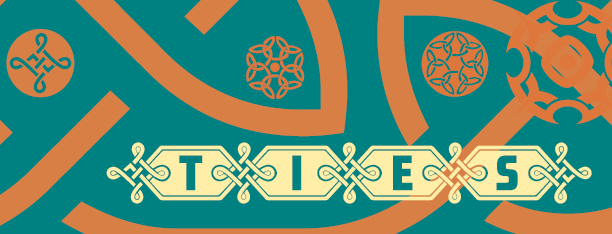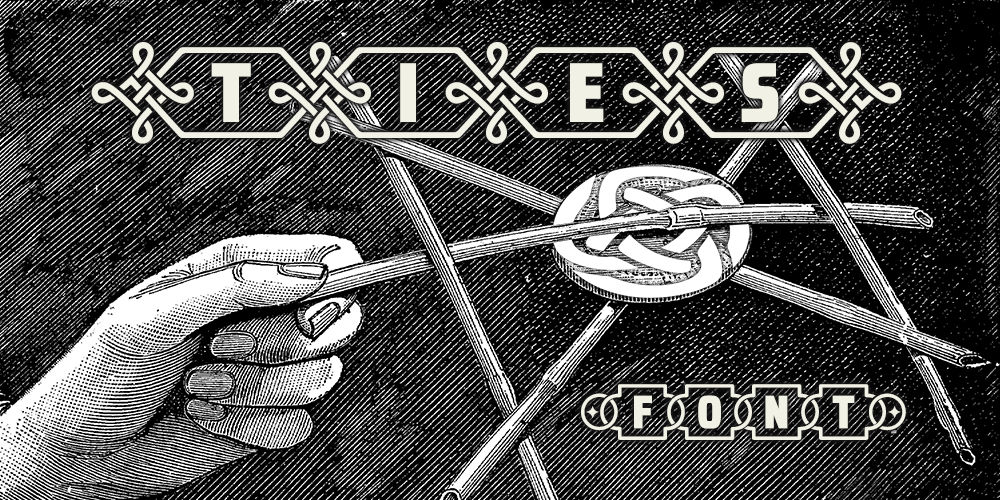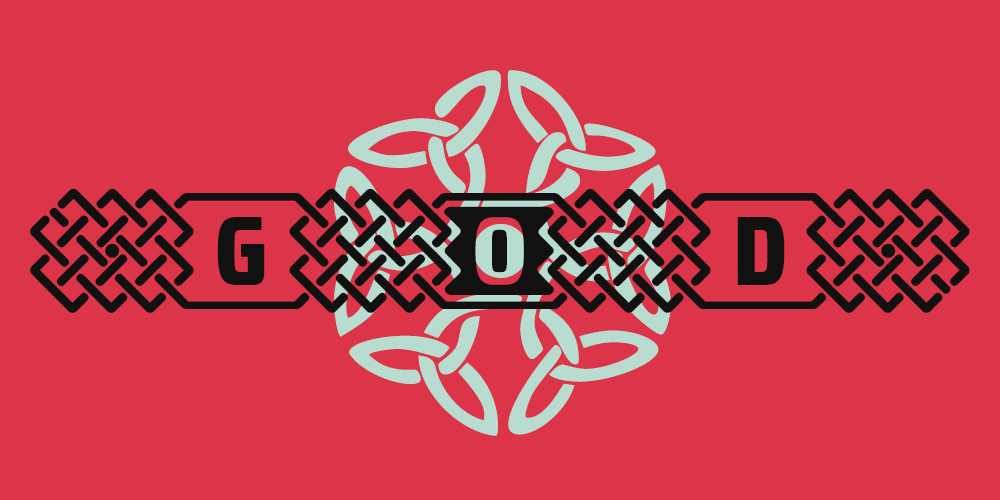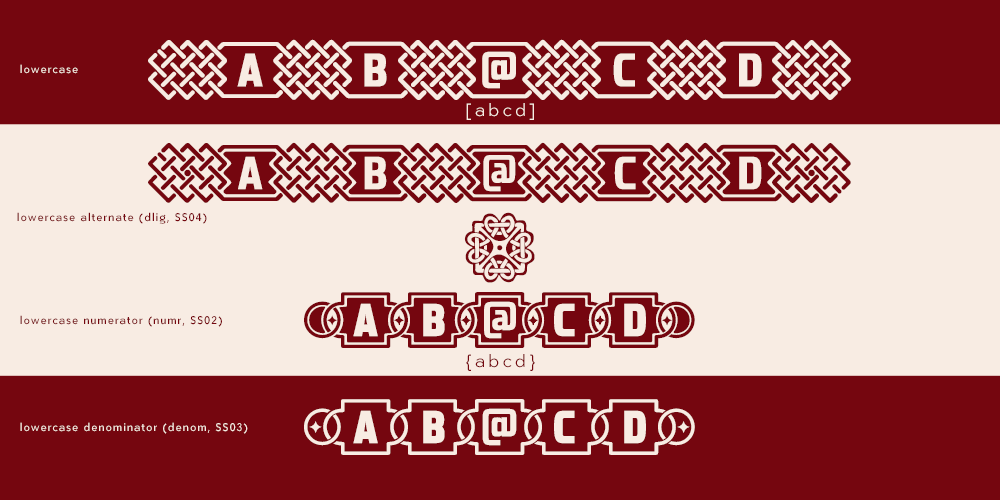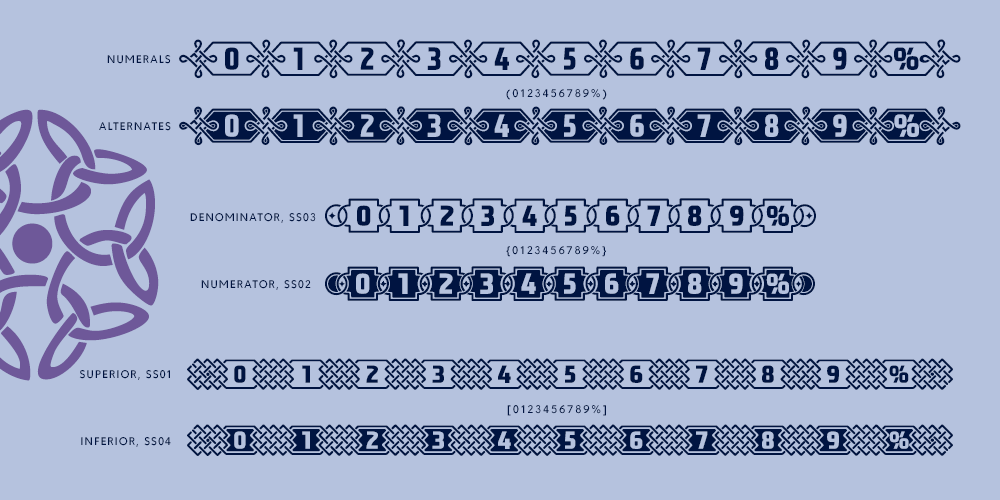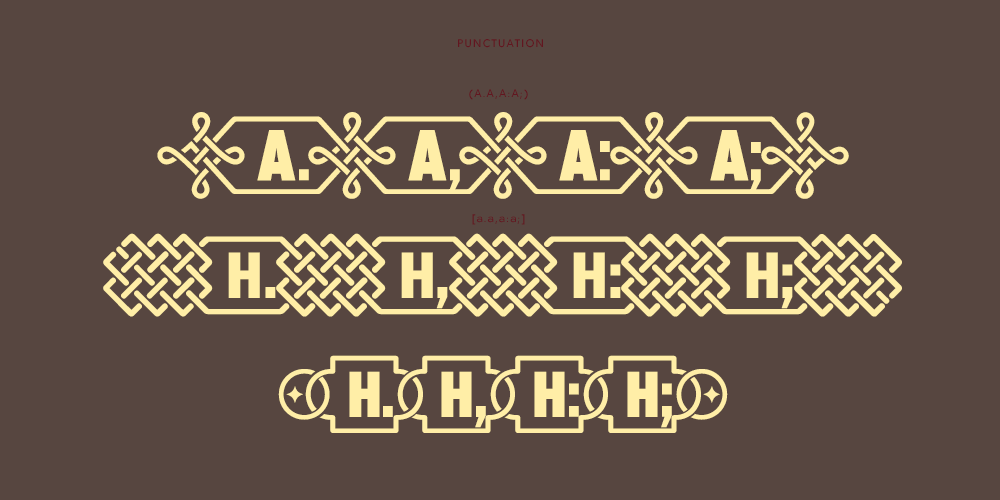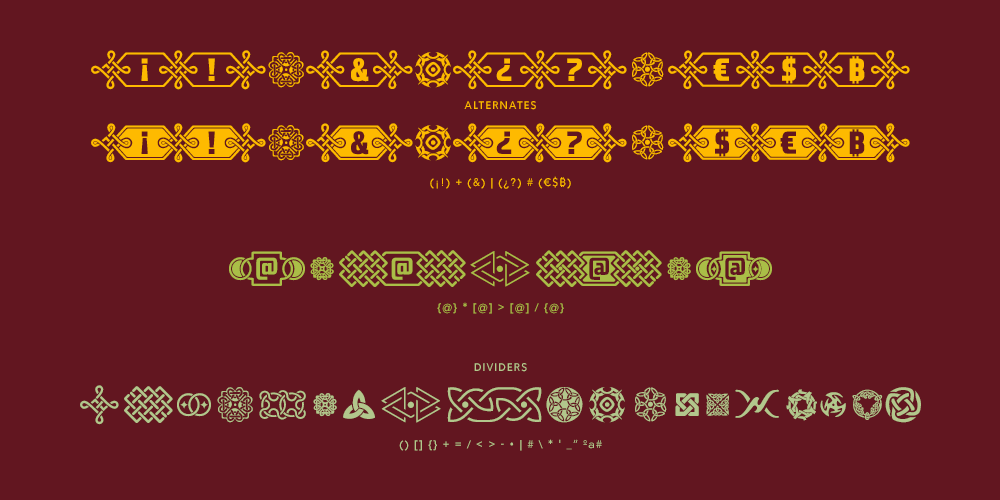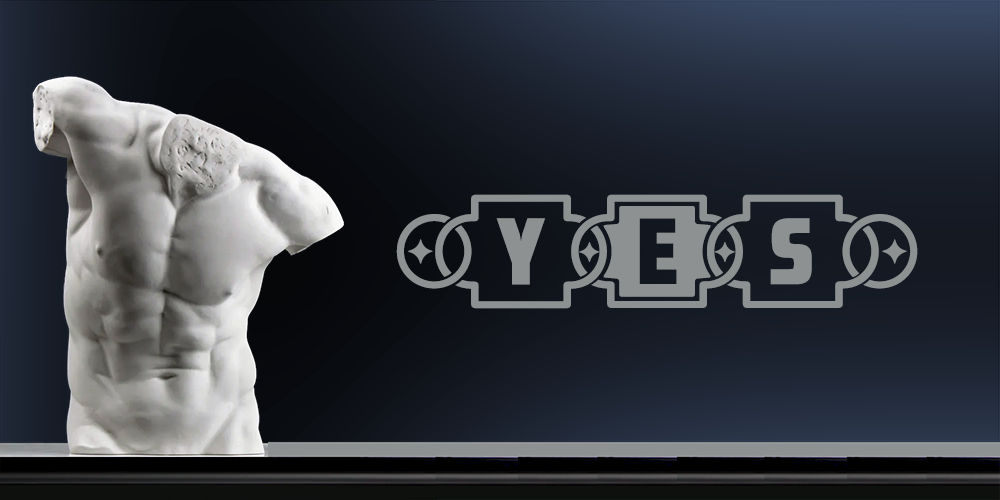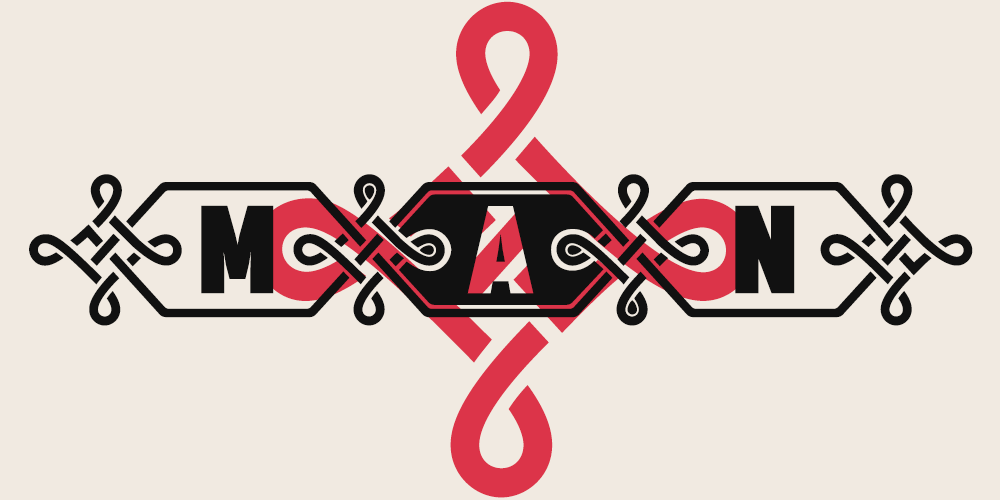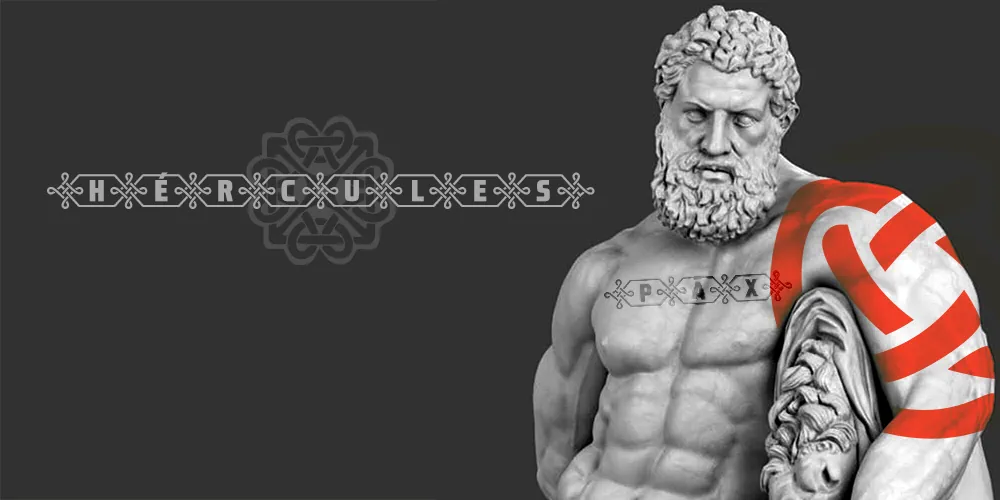
Banner font • Tribal Style • 06 styles
Estilo: Sans Serif, Capitals, Display, Layered, Eroded
Proporción: Condensed, Extra Bold
Glyphs: 567
Alternates: 220
Latin-Extended: Latín Básico, Europa Occidental, Central & Oriental.
Funciones OpenType: Additional languages, All Alternates, Bitcoin, Contextual Alternates, Denominators, Discretionary Ligatures, Inferiors, Numbers Small Caps, Numerators, Oldstyle Figures, Scientific Inferiors, Slashed Zero, Small Capitals, Standard Ligatures, Stylistic Set, Subscript, Superiors, Superscript.
El renacimiento de la banderola
Las tipografías banner o banderola tienen una larga tradición en el diseño decorativo. Históricamente evocaban letras talladas en madera o forjadas en metal que sostenían mensajes en estandartes y pendones. Su rasgo distintivo es el marco o contenedor que rodea cada letra, transformando el texto en un elemento gráfico en sí mismo: unifica las palabras y crea una pieza sólida e indivisible.
Más allá de comunicar un mensaje, funcionan como símbolos, emblemas o sellos que aportan presencia y estilo.
TIES Capitals retoma esta idea clásica y la lleva a un terreno contemporáneo, inspirado en el tatuaje, los ribbons y los patrones tribales.
Características técnicas
- Proporción: Condensada, con peso Extra Bold para máxima contundencia visual.
- Estilo: Todo en mayúsculas, Sans Serif, con un aire decorativo que fusiona lo tribal y lo moderno.
TIES está diseñada para brillar en proyectos editoriales y de alto impacto visual:
- Diseño editorial y folletos: Titulares, capitulares y citas destacadas.
- Pósters y cartelería: Ideal para conciertos, cine o eventos culturales.
- Packaging distintivo: Marcas que buscan transmitir autenticidad, fuerza o un espíritu artesanal.
- Identidad de marca: Naming, logotipos con carácter y piezas de merchandising.
- Diseño web: Hero banners, titulares de landing pages y gráficos para redes sociales.
TIES Caps es mucho más que una fuente: es un contenedor, un mensaje y un ornamento. Una tipografía pensada para quienes desean transmitir fuerza, unidad y un estilo visual capaz de atrapar miradas al instante.